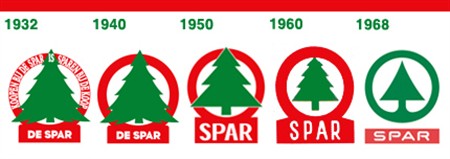
Schrift der Handelskette SPAR gesucht
mit den einschlägigen Font-Suche.Werkzeugen a la WhatTheFont habe ich es nicht geschafft. Vielleicht kann mir jemand von Euch weiterhelfen: Mit welcher Schrift wurde das SPAR-Logo gestaltet bzw. welche Schrift kommt der Verwendeten am nähesten?
Ich vermute auch mal ganz stark, dass Herr Loewy das Logo von Grund auf neu konstruiert hat und eher kein Cuttingedge-Ansatz verfolgt hat ;-)
"Der Schöpfer des heutigen SPAR Logos: Raymond Loewy(1893 - 1986)
Die endgültige Form des heutigen Logos wurde vom berühmten Designer Raymond Loewy 1968 entworfen. Es besticht durch Klarheit im Ausdruck und seine zeitgemässe Form. Raymond Loewy zählt zu den 100 einflussreichsten Amerikanern des zwanzigsten Jahrhunderts. Er war stets mit der hässlichen Form des Alltags unzufrieden und startete einen Feldzug des guten Geschmacks. Er verlieh zahlreichen Produkten - vom Bleistift über den Kühlschrank bis hin zu Fährschiffen - ein eindrucksvolles Design."
klar ist das ein font, die sparkasse hat doch das gleiche S :huhu:
Nö, auch nur entfernt ähnlich, wobei die gemeinsame Farbe weiß und rot noch zusätzlich zur Ähnlichkeit beiträgt.